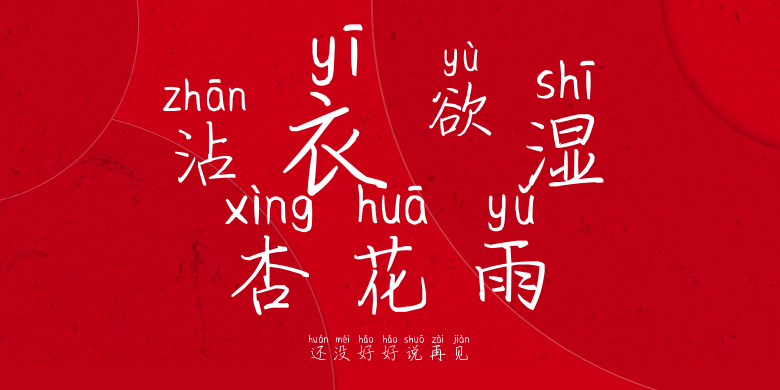
还没好好说再见
还没好好说再见,这款字体结构工整、笔画清晰,兼顾美观与易读性,适用于标题、正文、海报、包装、LOGO 等多种场景。字形优雅稳定,风格百搭耐看,适配日常排版与创意设计,让文字呈现更舒适、更具质感。还没好好说再见一笔一画,皆是细节,以均衡的比例、流畅的线条打造舒适视觉体验,字形端正大气,风格简约现代。无论是商业设计、品牌宣传还是日常排版,都能轻松驾驭,让文字更有格调与力量。还没好好说再见字体下载。